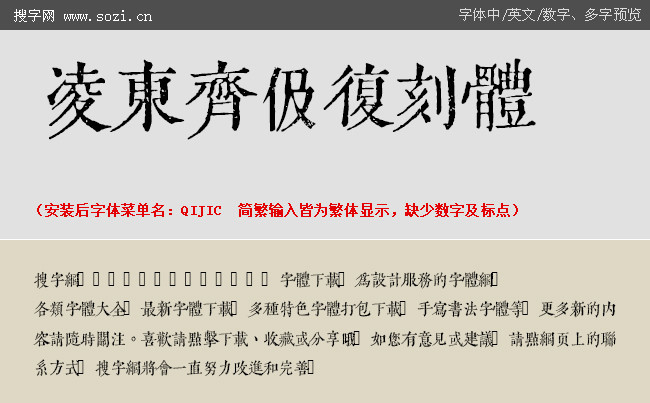
凌東齊伋復刻體
搜字網給大家提供一款凌東齊伋復刻體中文字體下載, 凌東齊伋復刻體采用半自動計算機視覺和OCR對《李長吉歌詩》和《淮南鴻烈解》進行掃描,通過程序處理后再手動選擇適合的字型,最后導出成字體文件,凌東齊伋復刻體是對古籍進行處理而得到的字體,所以只有繁體字形。在使用字體的過程中,如果輸入簡體字會直接映射成繁體字形。而且可以免費商用!適合海報設計、包裝設計等宣傳廣告等應用。